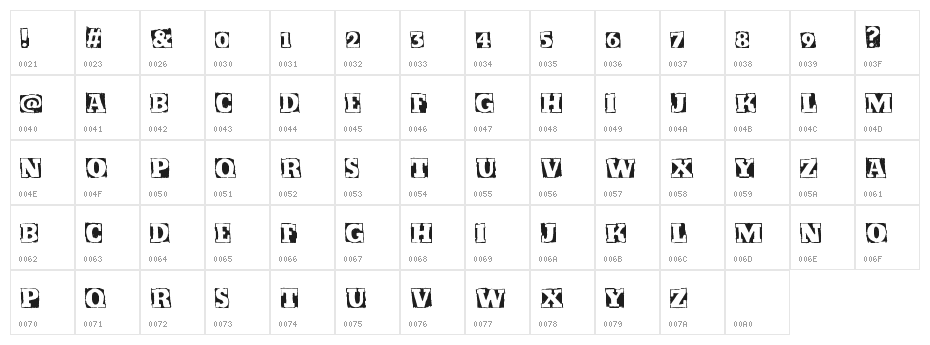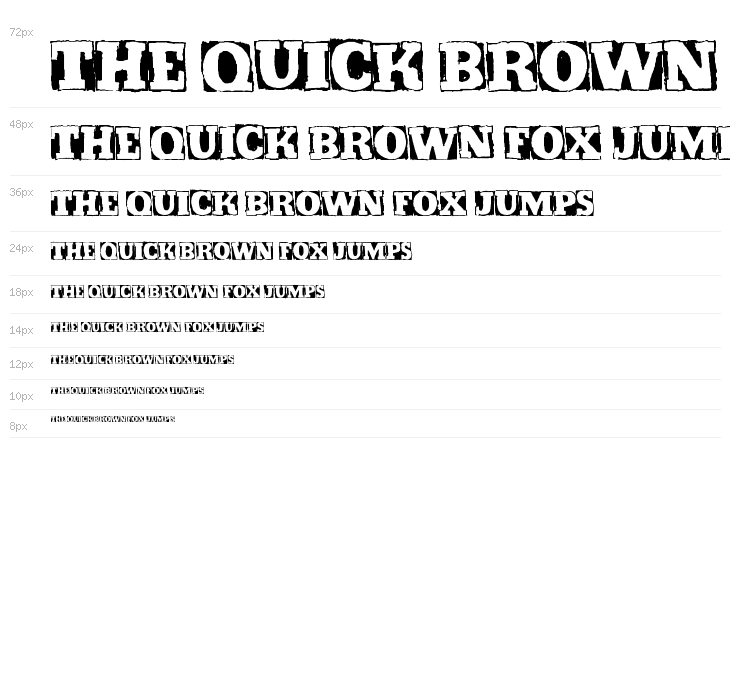
Kickstop Font
✎ Messy
| Progetti proposti | Ideal for posters, album covers, branding for edgy or industrial-themed products, and any design that requires a strong, impactful typeface. |